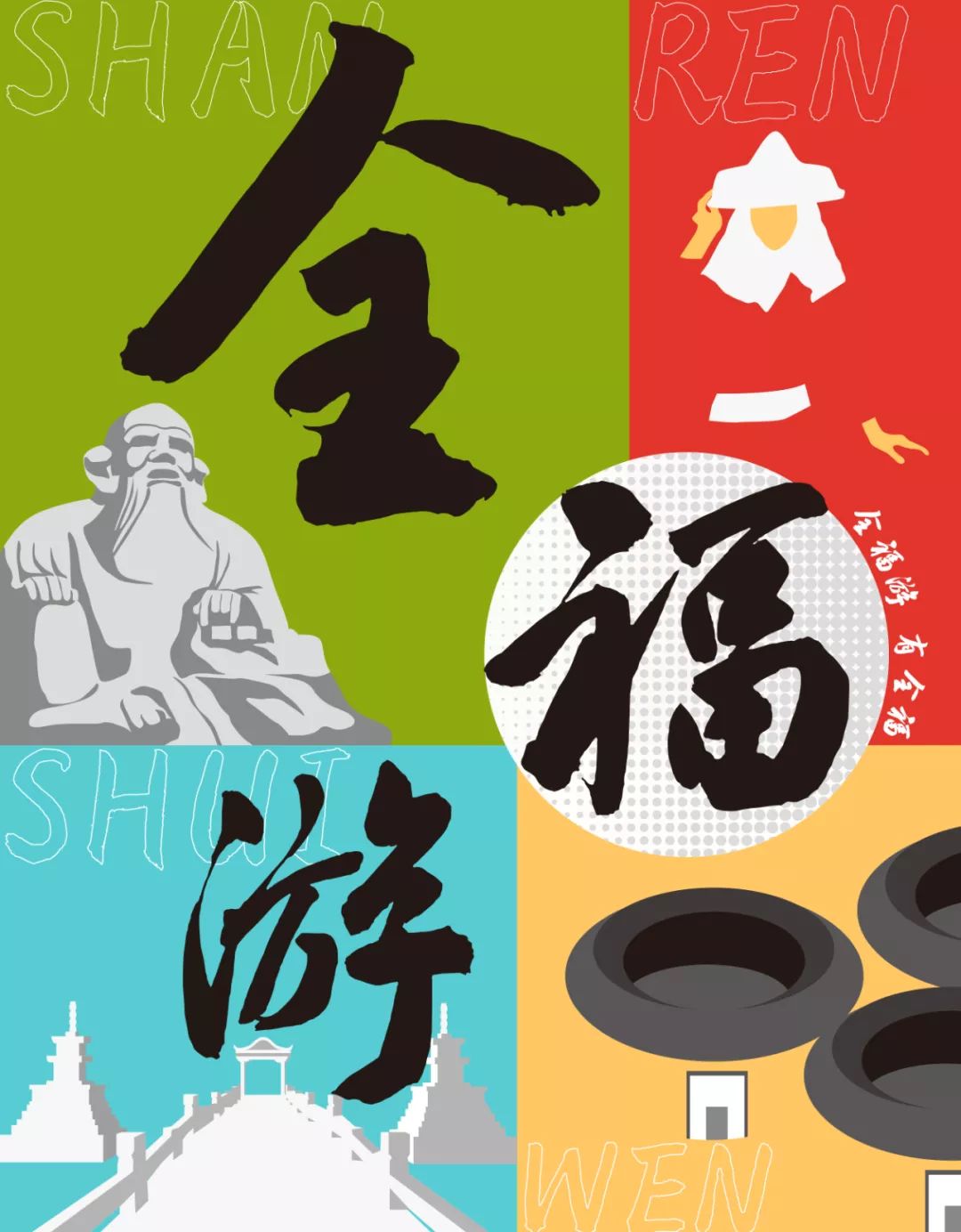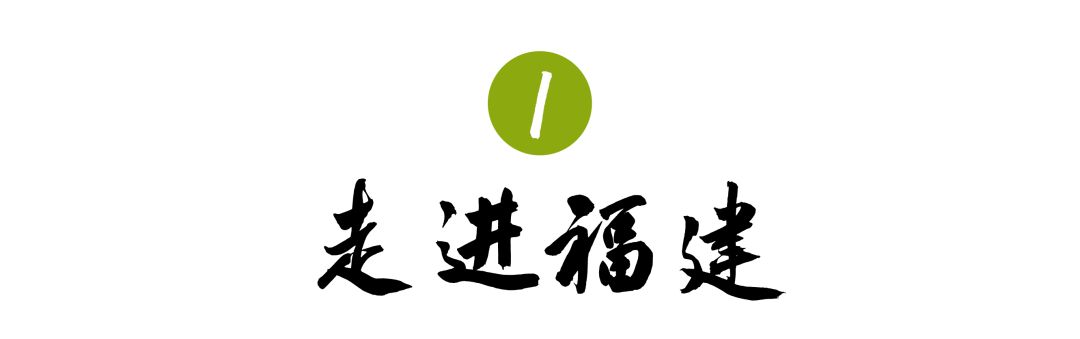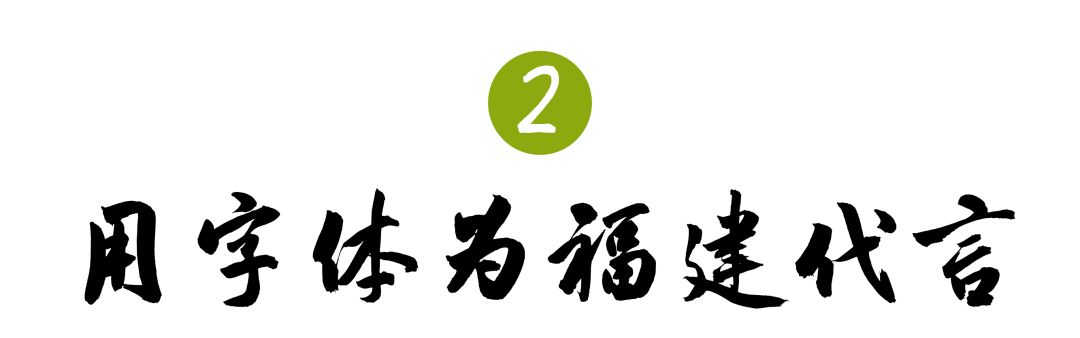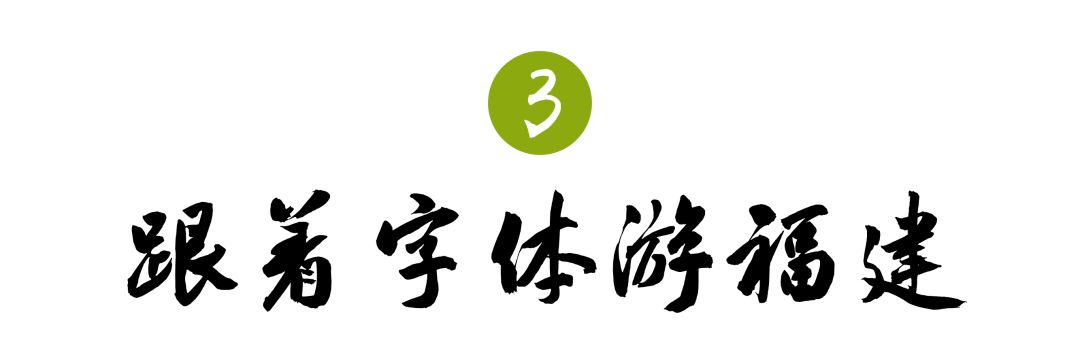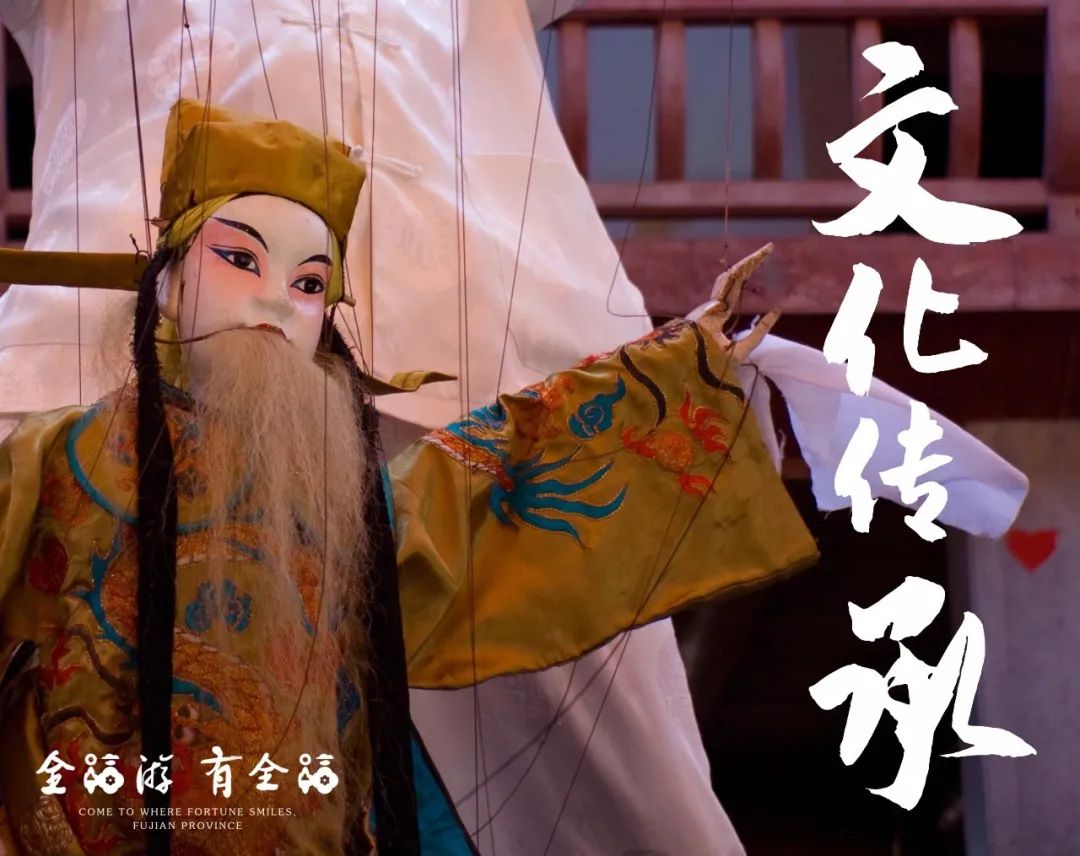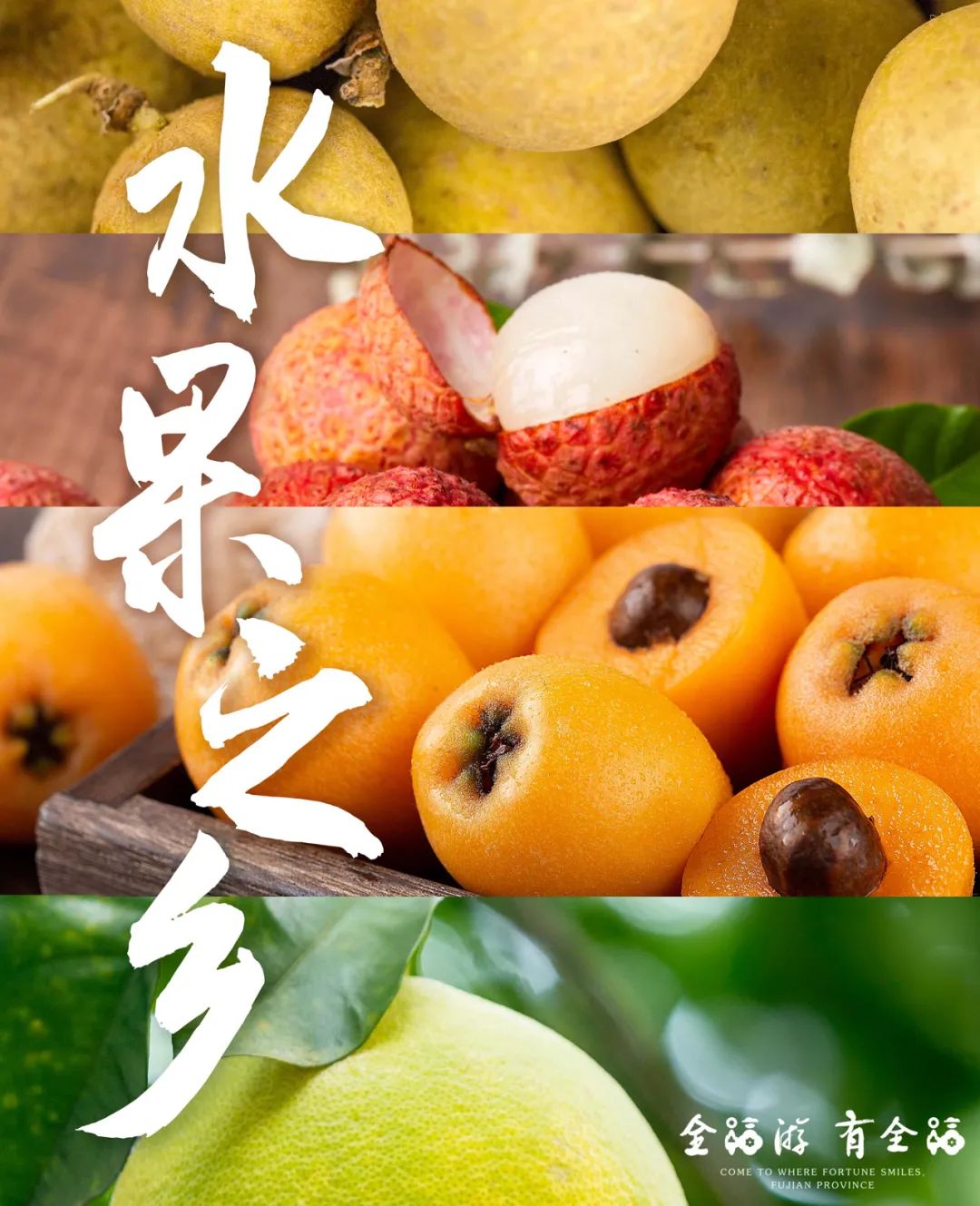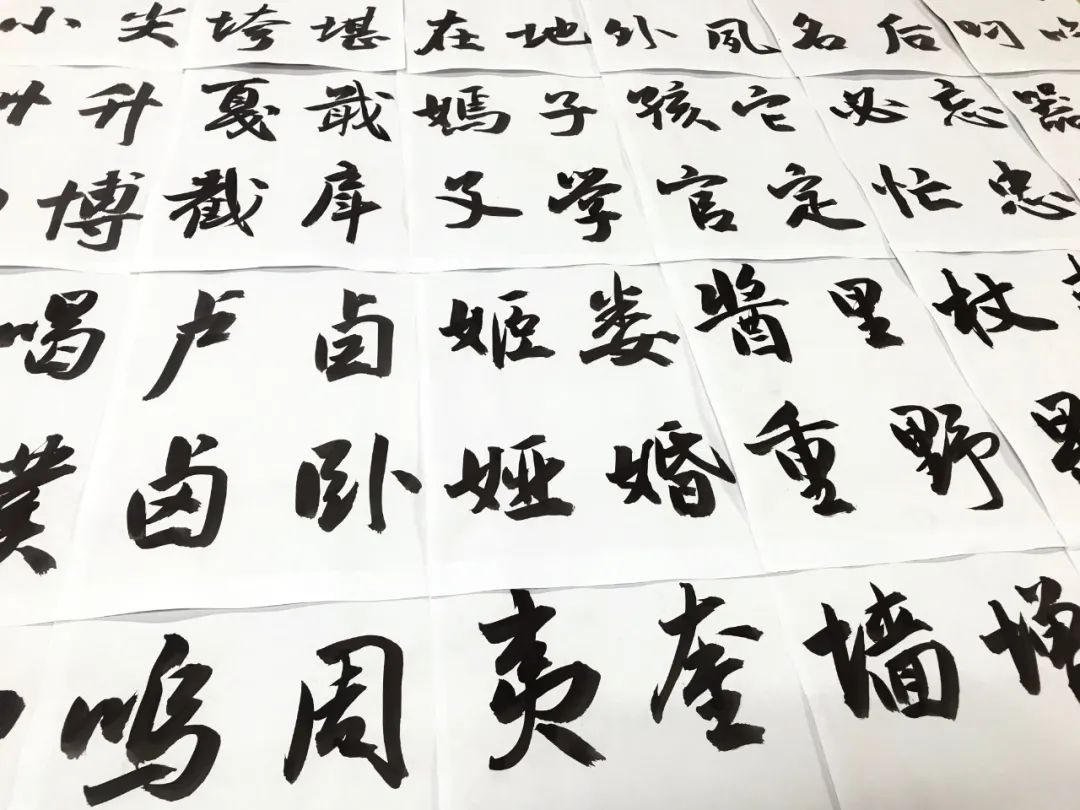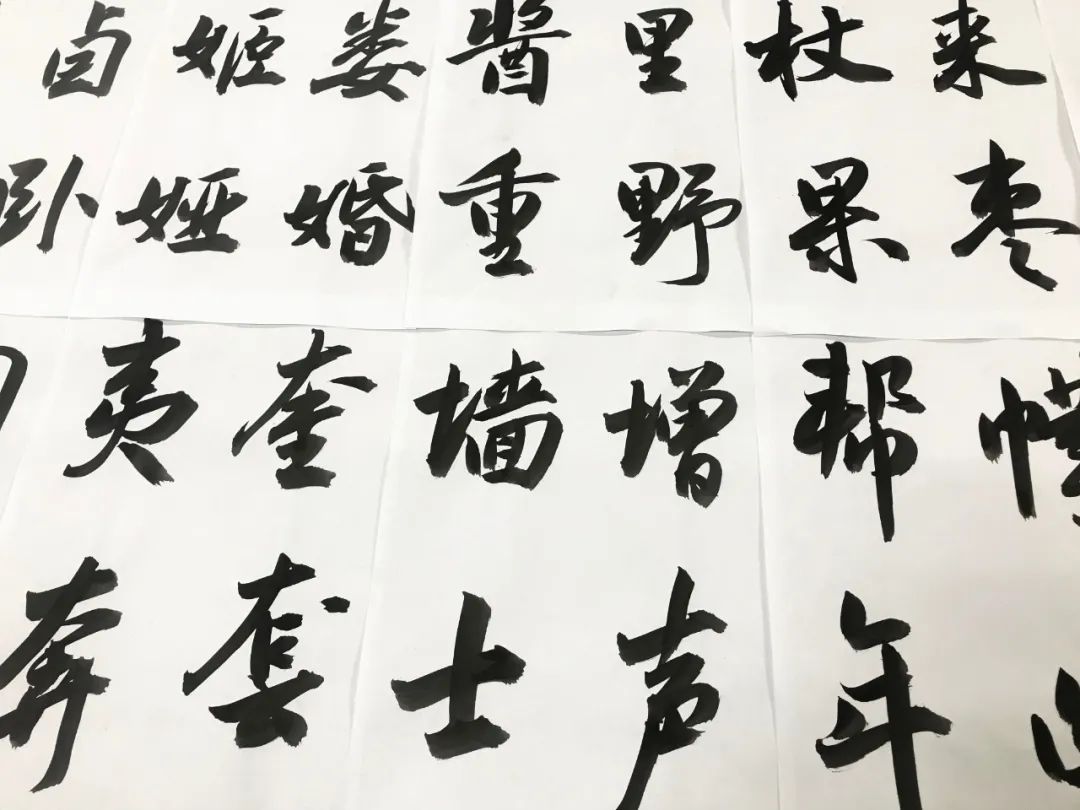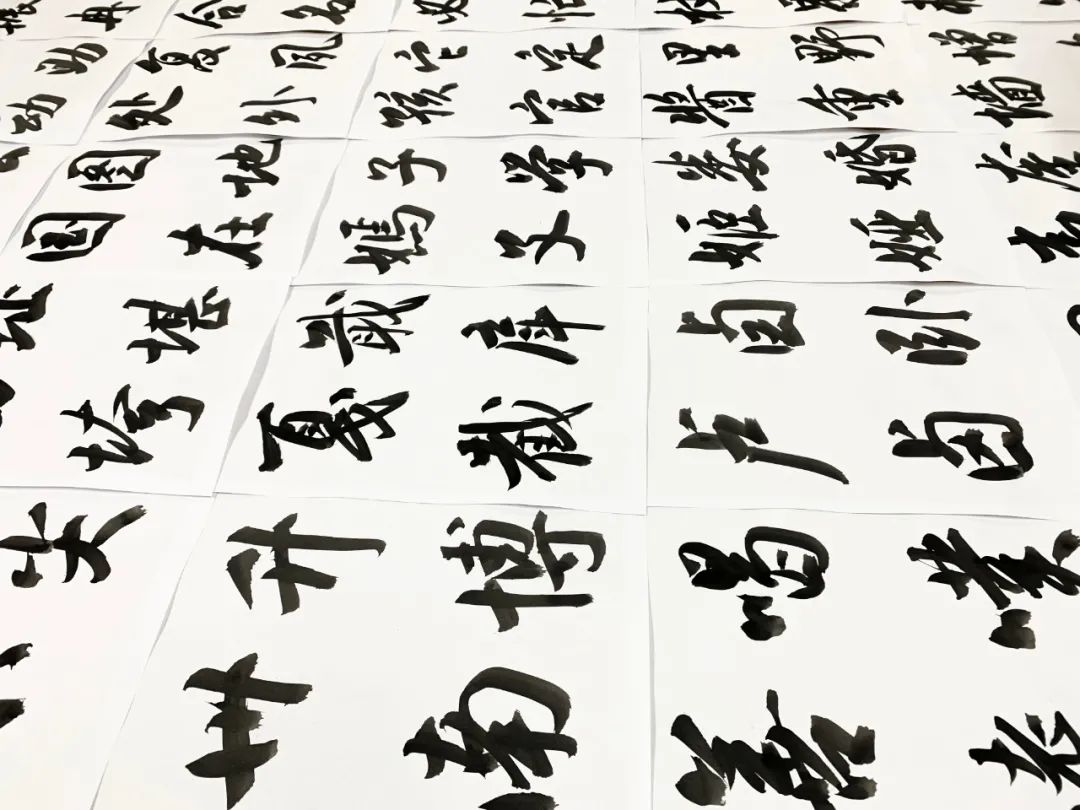
福建,一方历史悠久、华彩多元的东南福地,文化韵味浓厚却气质低调内敛。作为著名侨乡,福建拥有不可计数的文化名镇古村和传统村落;身处沿海地带,境内丘陵连绵,依山傍海,福建旅游资源丰富且独特、景色奇异秀丽。小资的福州,精致的厦门,古早味的泉州;三坊七巷,拐角就能遇见名人故居;鼓浪屿,琴声与涛声同在;武夷山,山顶云雾环绕;福建土楼,展示神秘的东方韵味;还有太姥山、清源山等国家AAAAA级旅游景区。
福建是文艺的,福建也是悠闲舒适的,美丽亦奋进,充满韵味;朴素、简单却幸福。但福建拥有的远不止这些,还有,朱子文化、茶文化、建筑文化……还有,肉燕、鱼丸、花生汤和鼎边糊等等遍地的美食,还有歌仔戏、布袋戏、闽南歌……不一样的娱乐休闲方式。闽式生活是甘甜的茶,质朴如初,蕴含治愈的力量。福建之美,浑然天成、内外兼在。“石红青兮百叠,山浓淡兮万重”,一缕清风,一捧清泉,这样的福建怎么能让人不心动?
为了更好地塑造福建的区域形象,体现福建文化旅游资源的丰富性与独特性,凸显“全福游、有全福”品牌,福建省文化和旅游厅与方正字库联合推出福建文旅厅系统专属的定制字体——“全福体”,这是方正首款区域性定制字体,也是国内首款由省级政府文旅管理部门定制的字体。
“全福体”是一款书法行书字体,由来自福建福州的方正字库设计总监仇寅书写设计。仇寅早在80年代就已享誉中国硬笔书坛,出版有《仇寅钢笔字》、《仇寅书外国名诗》、《古帖新临多体钢笔字帖》等多部字帖。加入方正字库后,创作出了方正大魏体、方正悠黑等多款蕴含书法底蕴、书写人文精神的字体。2017年起,仇寅担任中华精品字库工程设计总监,指导整理并创写设计了方正苏轼行书、方正米芾行书、方正赵孟頫楷书等多款精品书法字体。
仇寅老师写“福”
“全福体”部分字稿
“全福体”的设计,继承了“全福游,有全福”原始LOGO的厚重和毛笔书写韵律,受福建山水人文浸润三十多年的仇寅,在书写设计过程中,融合了宋代“尚意”书风的格调,并考虑字库的易识性、通用性,进行了多次书写尝试及优化调整,最终完稿的“全福体”给人以文雅、厚重、大气之感,雅俗共赏。
顿笔起,轻笔收,轻重之间的韵律美增强了字体的辨识度。顿笔入纸,笔画硬朗而稳重、挺拔刚劲、笔酣墨饱,将新时代新福建的良好形象融入字体的一笔一画中,寓意对福建文化事业茁壮发展的信心与希冀。轻笔收,收笔舒展而有延伸感,将对提升福建文化和旅游影响力的美好祝愿体现于字体细微处。折笔骨力强健,干净利索,刚性方折,转折处不露圭角,不见笔锋。字体线条的粗细变化丰富了文本的浓淡节奏,撇画一气呵成,捺则丰厚雍容,提画真率畅意,点画顿挫分明。疾笔与涩笔有机结合,迅畅而不失清晰的笔路,以轻松的执笔将福建的丰富性体现于字体细节中。笔画增添游丝,运笔行墨娴熟而精巧,一笔一画劲健洒脱、酣畅淋漓,有连贯之意,象征八闽山水连绵不绝、相互贯通。手写的方式,令“全福体”充满写意和人文气息,笔画间蕴藏着深沉而含蓄的力量,遒劲雅致而不失厚重大气,充分彰显了福建旅游文化的丰富、独特,以及深厚的积淀。
“全福体”结体秀美,结构轻松而充满生气,视觉上舒适亲切,既有古朴之感又符合现代审美,与福建区域文化的亲和、包容、多元相得益彰。
作为福建的名片,“全福体”开创了区域定制字体先河。它将"清新福建"独特的特征和记忆点融入字体的一笔一画间,可应用于各类传播媒介和公共空间,在城市形象宣传和推广方面都将产生微妙却不可小觑的影响力。“全福体”,通过字体所具有的传播属性,用特殊方式折射着福建这个区域的精神和理念,传播福建的美誉。
从明天起,做一个幸福的人,喂马、劈柴、周游世界。今天起,跟着“全福体”一起游福建吧。“游遍”清新福建,恋上“全福体”。福建,福见!